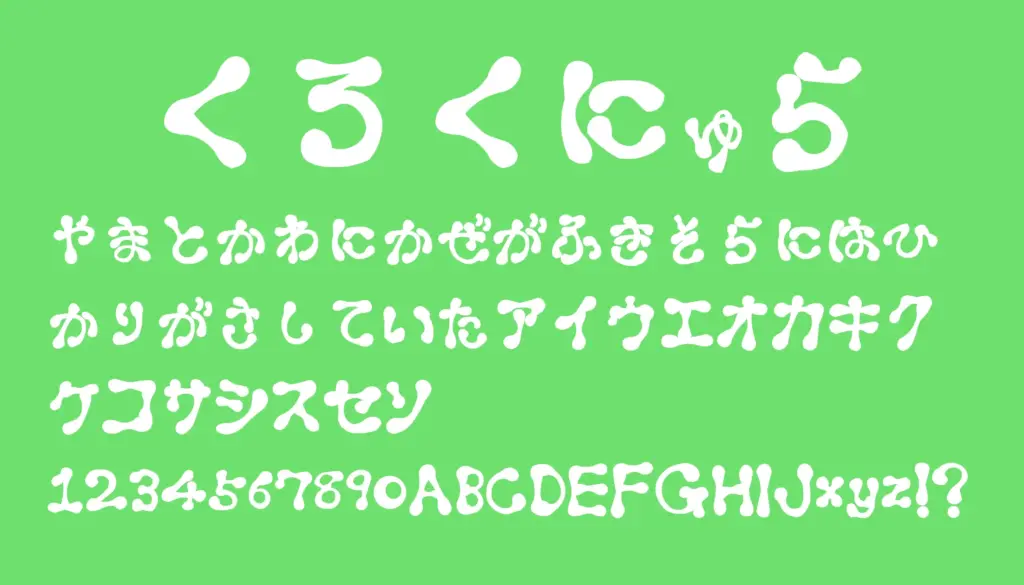
黒くてぷっくりとした見た目が特徴の、ユーモラスで愛嬌たっぷりなフォントです。にゅるっとした筆致がどこかコミカルで、やわらかさと弾力感をあわせ持つ文字デザインは、ポップなタイトルや子ども向けのコンテンツ、遊び心のあるグラフィックにぴったり。カタカナ・ひらがな・アルファベットの一部に対応しており、にぎやかな雰囲気を演出します。
くろくにゅら